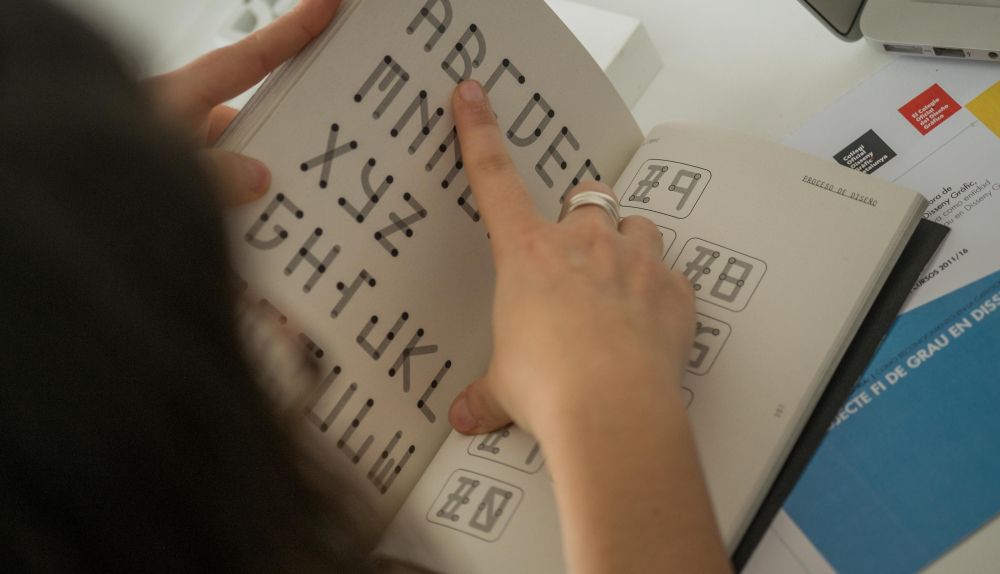
Es mujer, joven, jerezana y ganadora del premio nacional de Proyecto Fin de Grado en Diseño Gráfico que otorga el Colegio Oficial de Diseño Gráfico de Cataluña, la única colegiatura de España. Aunque a veces sienta que en su propia tierra su trabajo está infravalorado por el simple hecho de ser del Sur, Nuria López ha sido galardonada por haber realizado el mejor TFG de los 100 proyectos que han sido finalistas en el certamen catalán. "Y paradójicamente mi trabajo no tuvo ni la mejor nota de la clase", ríe. Nuria lleva cerca de 11 años de formación en el mundo del arte, pero el talento lo tiene desde pequeñita. Estudiante de la Escuela de Arte de Jerez, terminó en 2016 el grado de Enseñanzas Artística Superior de Diseño, en la misma escuela. Pero antes de finalizar su carrera, comenzó en 2013 unas prácticas en Salvartes, empresa local que a día de hoy sigue siendo su lugar de trabajo.
En una de las mesas del estudio jerezano, Nuria expone su proyecto de fin de grado. En líneas generales, la joven ha diseñado una nueva tipografía que incluye el sistema braille, uniendo así ambos alfabetos. "Se trata de una vía para unir las dos lenguas. Para no vetar a un público y no hacer discriminación entre ambos. Con este diseño que he inventado se ahorrarían costes, porque por ejemplo, en los ascensores no habría dos botones, sino solo uno donde aparezca el dígito y el sistema braille", explica. "Sí, se trata de diseñar gráficamente para ciegos", continúa.
Dice que cuando expuso su proyecto en la Escuela de Arte, muchos la miraban "con cara de loca", menos su tutora, Marta Villoslada, quien desde un primer momento apostó por su trabajo. Pero, ¿cómo se le encendió la bombilla? "Mi abuelo acabó casi ciego, por el azúcar. No sé si inconscientemente lo he hecho por él... Aunque yo creo que el detonante fue un día, mirando los ascensores", sonríe. La diseñadora jerezana destaca que no quería hacer un proyecto común que se pareciera a los trabajos que anteriormente había realizado y pensó que su TFG debía ser como "una conclusión de cómo entendía yo el diseño".
"Quise utilizar el diseño como herramienta para hacer algo, para ayudar, para cambiar algo". Y de algún modo, su trabajo "nace como protesta". Aunque el TFG se lleva a cabo en los tres últimos meses del curso, Nuria comenzó a trabajar en él desde noviembre de 2015, ya que cuando eligió su temática, su mente estaba en continuo funcionamiento y tenía la imperiosa necesidad de ponerse manos a la obra. Investigó el diseño como herramienta social, entrevistó a algunas personas ciegas con la ayuda de la ONCE, se empapó de investigaciones sobre la ceguera, hojeó estudios de la historia del brialle, consultó si el sistema actual era restrictivo con esta comunidad y leyó, leyó mucho. La joven diseñadora quiso ir más allá y lo consiguió.
En la gala, celebrada el pasado 21 de febrero, Joan Costa, un referente en el mundo del diseño en España y a nivel internacional, fue quien le otorgó el premio, con el cual Nuria ha podido registrar la marca y la patente de su tipografía, además de dos años colegiado. "Estando colegiada te toman más en serio", incide, al tiempo en que comparte que hasta la fecha no ha sufrido sexismo, pero sí discriminación por su lugar de procedencia. "No te miran igual que si fueras catalán. Por el tema del acento, el tópico del vago... Ahora cuando trabajas empresas grandes en Madrid, notas que alguno te trata en plan: a ver si los perritos andaluces pueden solucionar las cosas. Y claro, cuando ven que eres profesional...".
La diseñadora jerezana adelanta que le gustaría continuar con su trabajo haciendo un doctorado: "No me importaría, es un tema chulo que sigo teniendo en la cabeza". Y en este sentido, también le encantaría que su tipografía se trasladase al escenario público. "Pero el problema es que en cosas de estas, se invierte poco", concluye.